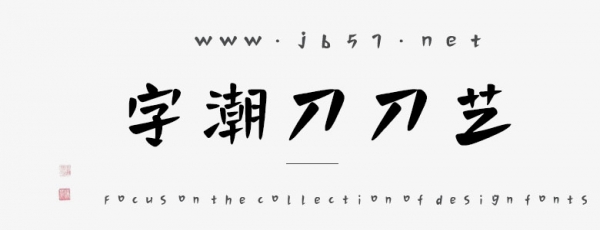
字潮刀刀藝是由字潮字庫(kù)出品的字體,這款字體筆觸略粗,字形圓潤(rùn),略顯可愛(ài),具有很好的視覺(jué)感,適合應(yīng)用于藝術(shù)設(shè)計(jì)、平面宣傳設(shè)計(jì)、網(wǎng)頁(yè)設(shè)計(jì),書法字帖等領(lǐng)域,需要的朋友可以前來(lái)本站下載。